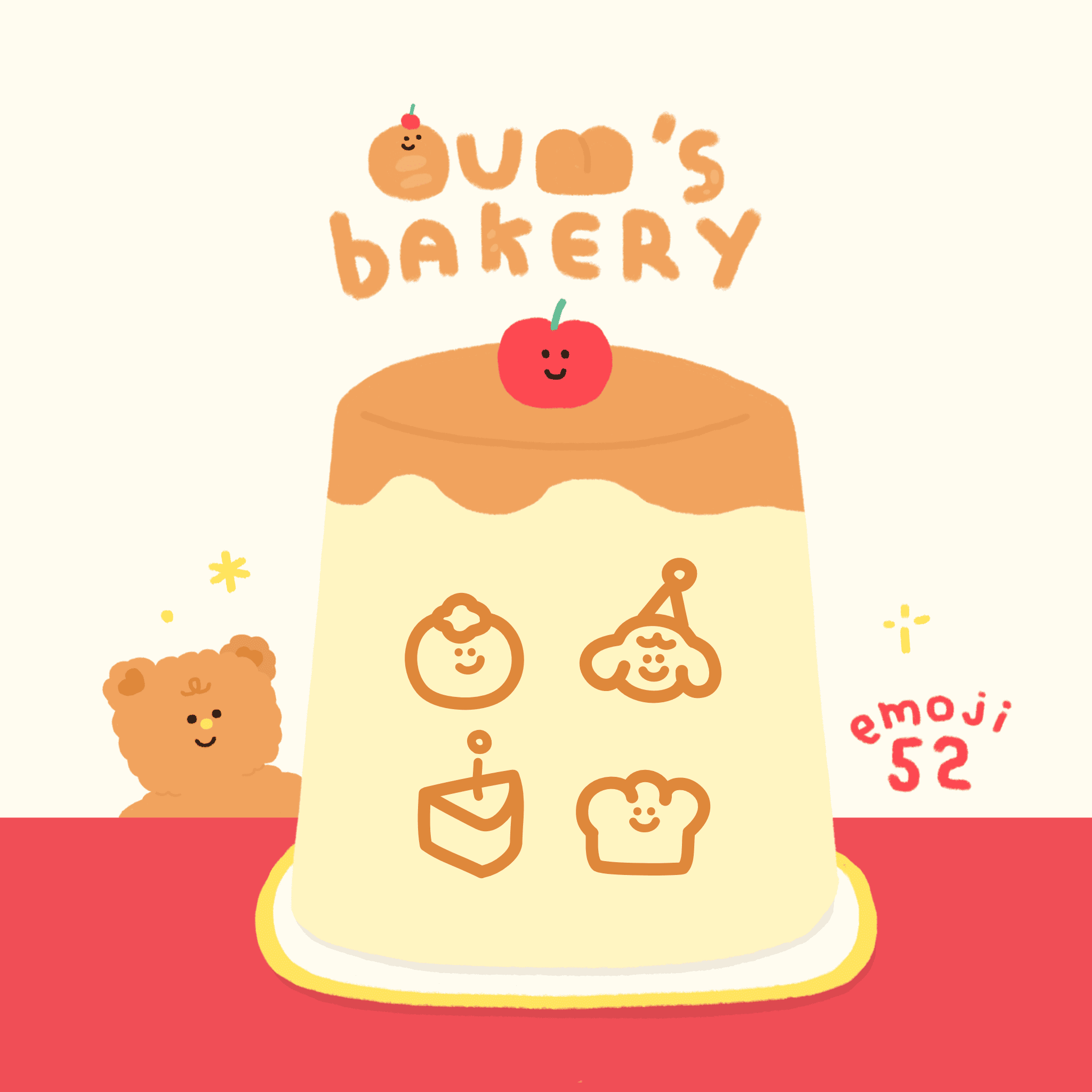
OUMISHAPPYY | FONT (oum’s bakery emoji)
ฟอนต์อิโมจิล้วนที่ทุกคนขอมามากที่สุด! พาน้องๆอิโมจิจากฟอนต์ต่างๆมารวมกัน บวกเพิ่มไปกับน้องอิโมจิหน้าใหม่อีกเพียบ รวม52ตัวไปเลย น่ารักล้นจอแน่นอนค้าบ